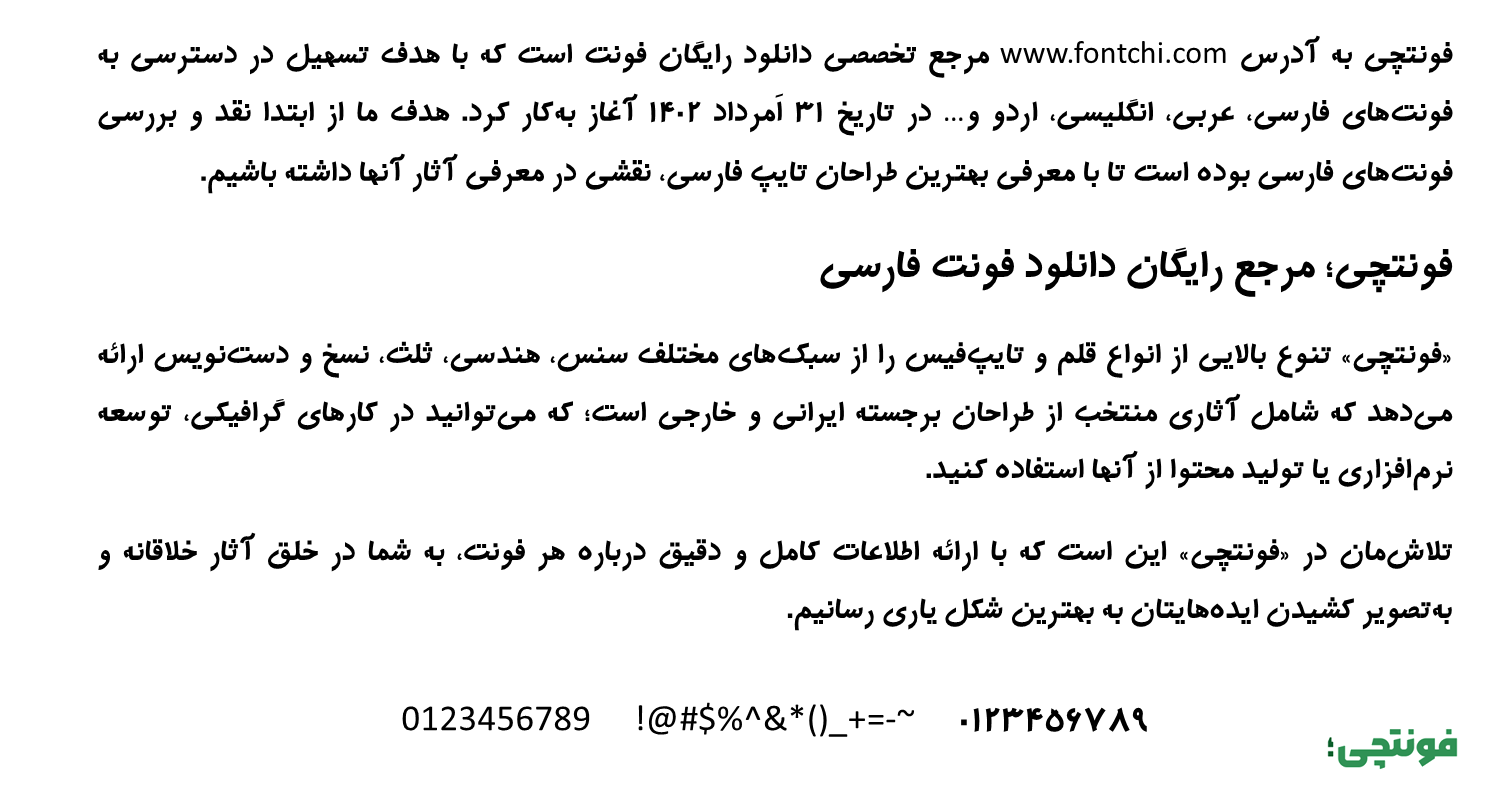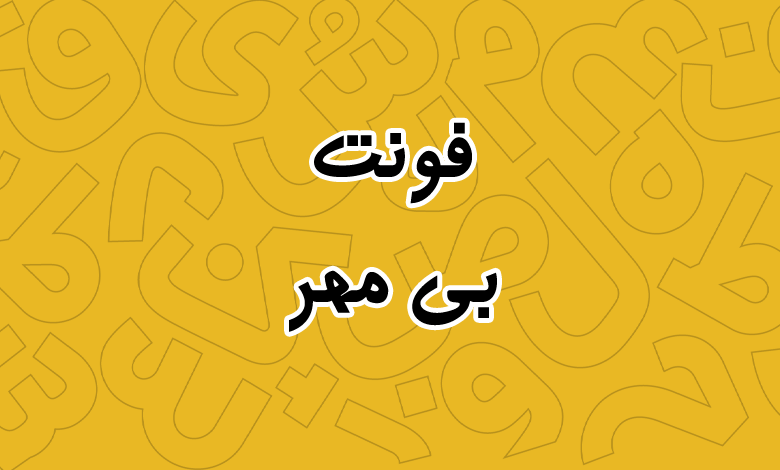
فونت بی مهر (B Mehr)
فونت بی مهر یا فونت مهر (به انگلیسی: B Mehr) یکی دیگر از فونتهای آزاد مناسب برای عناوین و تبلیغات است که در دهه ۷۰ توسط برنا رایانه طراحی شده است. این قلم که دارای ظاهری فانتزی است میتواند برای کارهای نمایشی مورد استفاده قرار گیرد. در ادامه با دانلود رایگان فونت بی مهر همراه شما هستیم.
فونت b mehr توسط برنا رایانه در دهه هفتاد با یک وزن بولد طراحی شده که با هدف استفاده در عناوین میتوانید از آن بهره ببرید. این فونت دارای فرمت TTF است، اما سایر فرمتهای آن توسط فونتچی نیز در بسته دانلود قرار گرفته است.
فونت فارسی بی مهر از این زبان پشتیبانی کامل دارد و بهلطف یکسان بودن با رسمخط عربی میتوانید برای زبان عربی نیز از این قلم استفاده کنید. کلیه گلیفهای متفاوت زبان عربی شامل اعراب، برخی حروف دارای دو نقطه و اعداد «۰۴۵۶» توسط این قلم پشتیبانی میشوند.
این فونت فارسی رایگان برای زبان انگلیسی فاقد طراحی اختصاصی است و از یک فونت معمولی لاتین برای آن استفاده شده است. لذا در صورتی که نیاز به فونت لاتین مناسب برای این قلم هستید پیشنهاد میشود با مراجعه به صفحه دانلود فونت انگلیسی، گزینه مناسب و نزدیک به این قلم را انتخاب کنید.
فونت بی مهر بولد تنها وزنی است که در این قلم استفاده شده است. این وزن برای استفاده در متون کوتاه انتخاب مناسبی خواهد بود که با هدف داشتن یک فونت نمایشی مورد استفاده قرار میگیرد. از همینرو میتوانید برای کارهای مختلفی همچون چاپ روی بنر، مطبوعات، فونت عنوان کتاب و فونت برای مجلات از این قلم استفاده کنید.
تمامی حروف در فونت بی مهر دارای ظاهری فانتزی و ضخیم هستند. بهطوریکه انتهای حروفی مثل «ت، ن، ل، ق، ی، س، ش، ص، ض» دارای کشیدگی بوده و همچنین زاویهای به صورت کج به سمت راست دارند. گودی ها نیز در حروفی مانند «ل، س، ش، ن» بهصورت مورب هستند. بر خلاف دیگر فونتهای سری بی، در این فونت نقطهها مربعی هستند.
چنین ویژگیهایی این فونت را برای استفاده در شبکههای اجتماعی برای تامنیل ویدئوها و پستها به انتخاب خوبی تبدیل کرده است. اگر به دنبال فونت فارسی برای کپ کات رایگان هستید، میتوانید از این قلم استفاده کنید.